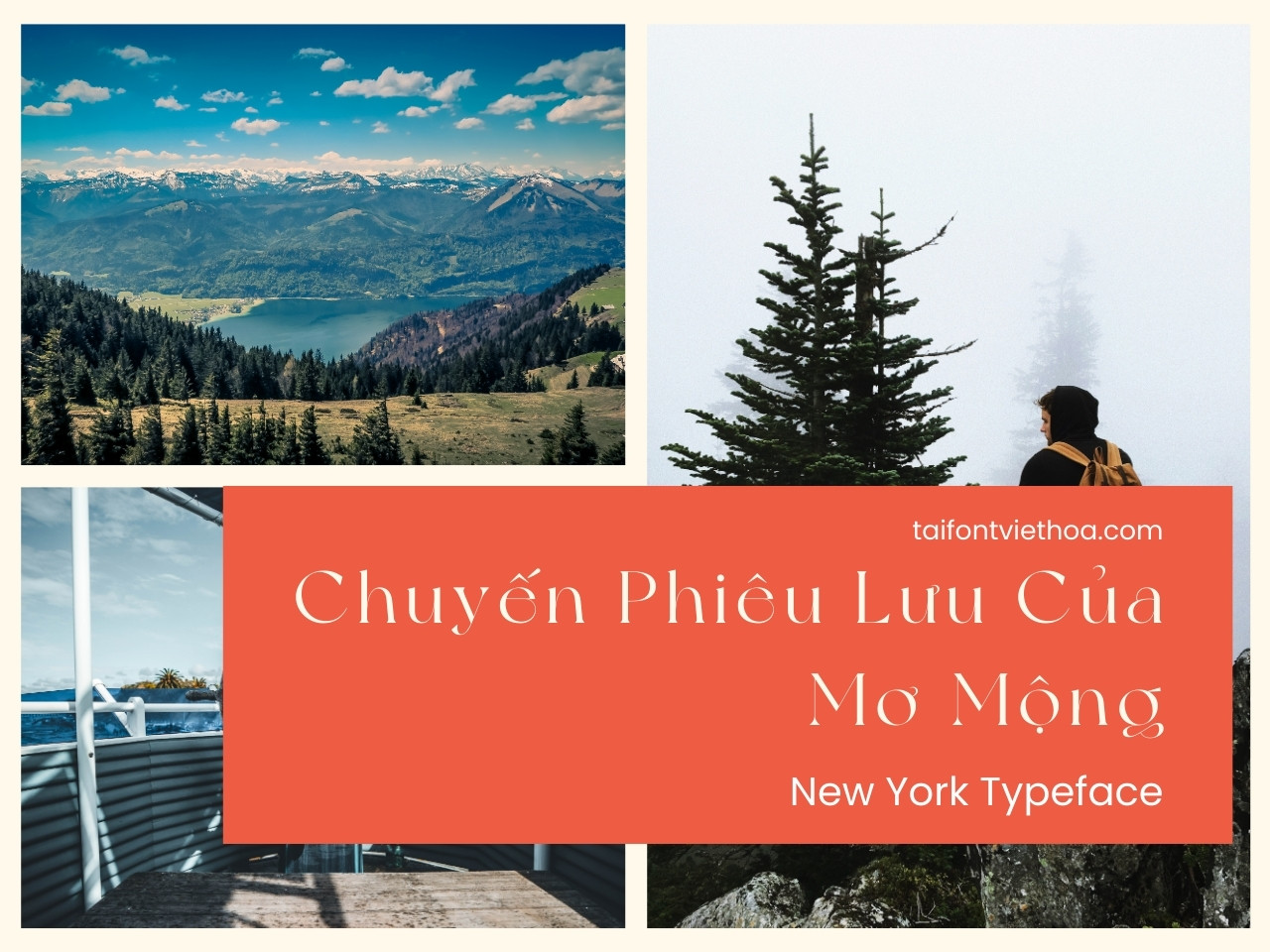
Font việt hóa New York
Tác giả Font: Artem Nevsky
Giới thiệu về font New York
New York là một font serif hiện đại, được phát triển dựa trên tinh thần thanh lịch và cổ điển của các kiểu chữ truyền thống. Đây là một phần trong hệ sinh thái font của Apple, từng được giới thiệu lần đầu tiên trong bộ giao diện macOS Catalina và được thiết kế để tối ưu khả năng đọc trong môi trường kỹ thuật số. Bản Việt hóa của font New York được thực hiện bởi March Nguyen, đảm bảo đầy đủ dấu tiếng Việt, giúp người dùng tại Việt Nam có thể sử dụng linh hoạt trong các dự án sáng tạo. Bên cạnh tiếng Việt, font còn hỗ trợ hơn 50 ngôn ngữ khác thông qua bảng mã Latin, Latin Extended. Font này đã được taifontviethoa.com chọn lọc, sưu tầm và kiểm tra thực tế qua nhiều dự án thiết kế nhằm phục vụ cộng đồng thiết kế và sáng tạo nội dung.
Đặc điểm thiết kế và ứng dụng của New York
New York sở hữu đường nét chắc chắn, đối xứng với phần chân chữ thanh mảnh nhưng dứt khoát, mang đến cảm giác sang trọng và tinh tế. Font có độ tương phản cao giữa các nét dày và mảnh, đi kèm các chi tiết serif rõ ràng, giúp tăng khả năng đọc khi dùng ở kích thước nhỏ. Font phù hợp để làm tiêu đề, nội dung bài viết, tài liệu học thuật hoặc các ấn phẩm in ấn cao cấp.
Font New York lý tưởng cho các ứng dụng như thiết kế tạp chí, sách in, bao bì sản phẩm cao cấp, bộ nhận diện thương hiệu, thời trang và các dự án sáng tạo mang hơi hướng cổ điển. Font đặc biệt phù hợp với các ngành như truyền thông, giáo dục, xuất bản, mỹ phẩm cao cấp và quảng cáo sang trọng.